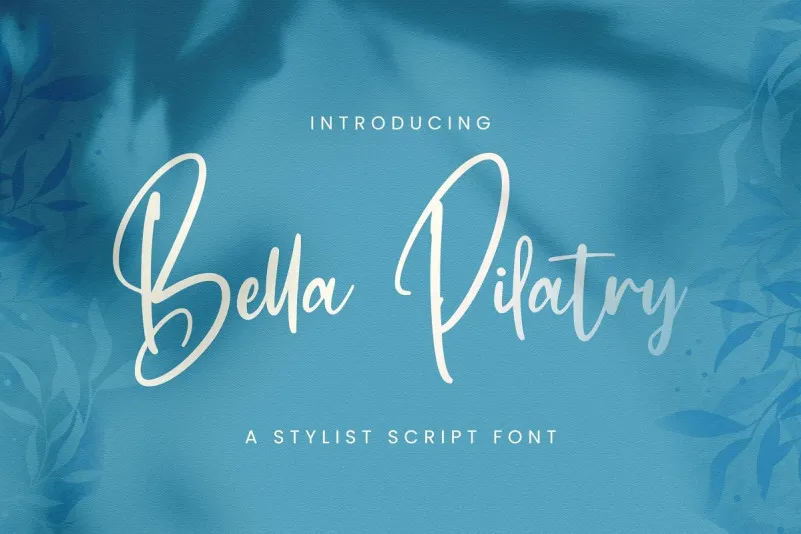
Bella Pilatry Font – Download Grátis
A Bella Pilatry Font é uma assinatura do tipo script que transmite estilo através da caligrafia. Ela foi criada pela StringLabs e incorpora caracteres belos e equilibrados, proporcionando um visual agradável que se combina com diversas ideias de design. Esta fonte atende aos amantes da criatividade e do bom gosto, oferecendo uma experiência única na criação visual. Seja para um site elegante, ou até mesmo para um projeto gráfico original, Bella Pilatry trará vida à sua concepção. Experimente transformar suas ideias mais inusitadas em realidade com esta fonte de script.